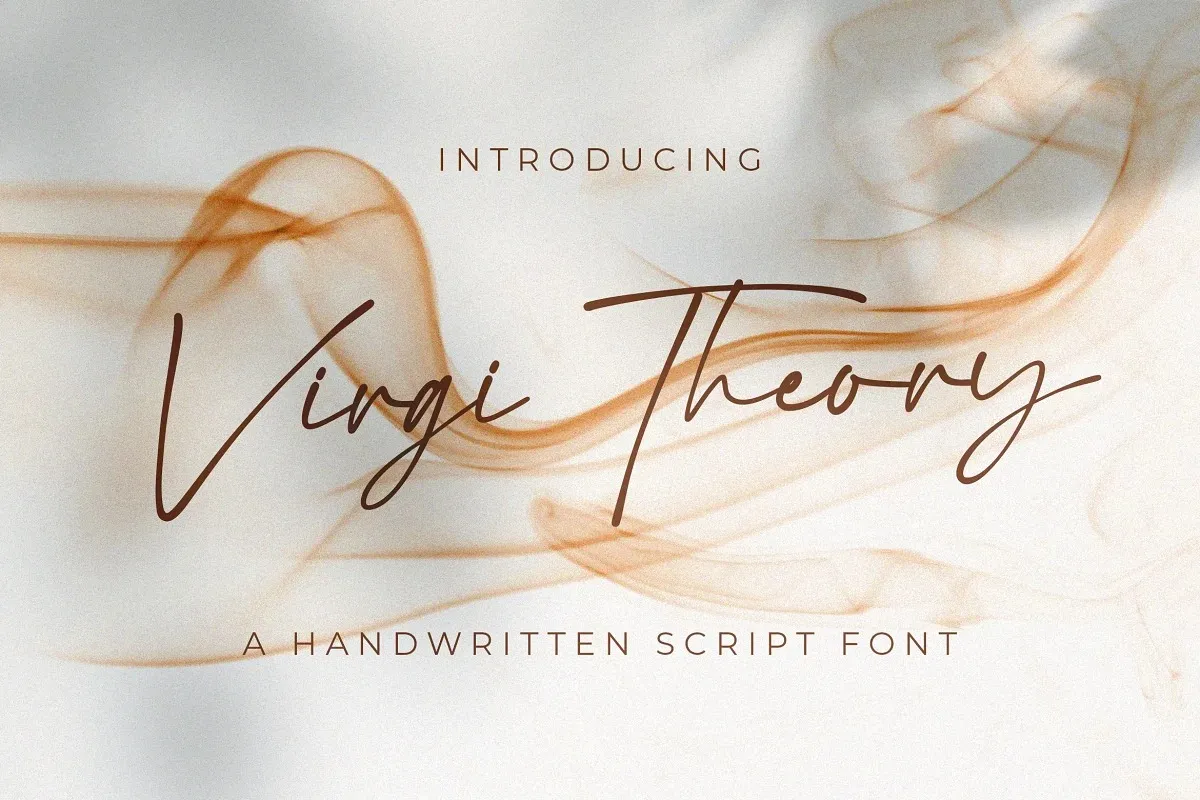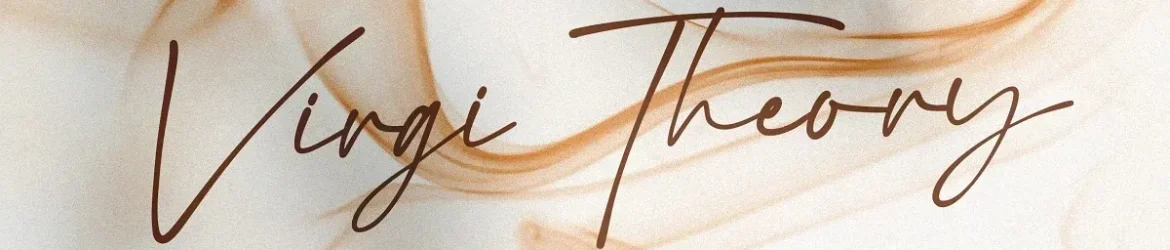
A fonte ‘Virgi Theory’ é uma escrita cíliada com um fluxo natural e moderno. Ela tem caracteres belos e bem equilibrados, o que permite que se adapte a uma ampla gama de design. É ideal para aqueles buscando um estilo único para seus projetos criativos, ajudando-os a dar vida aos seus conceitos mais audaciosos. Com sua elegância e modernidade harmoniosas, esta fonte é perfeita tanto para aplicações digitais quanto impressivas, tornando-a uma escolha ideal para aqueles que querem destacar-se em qualquer tipo de projeto visual.